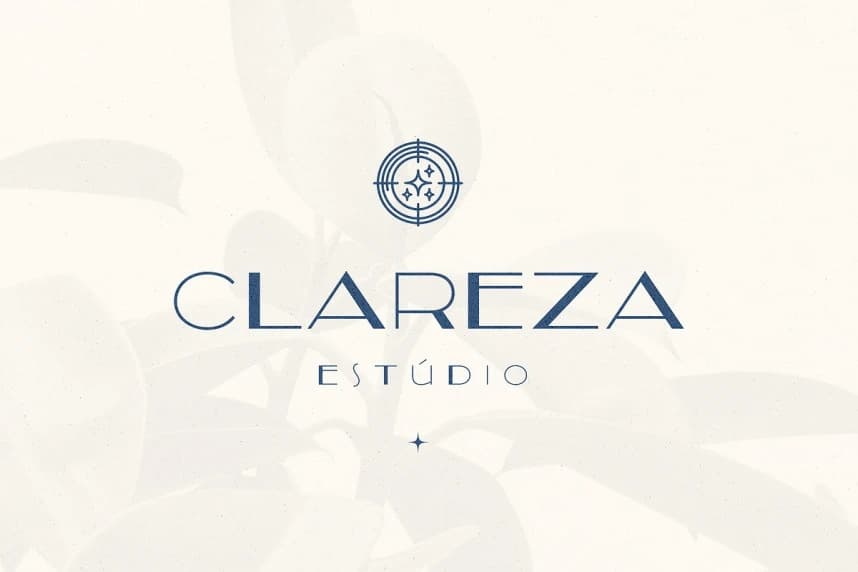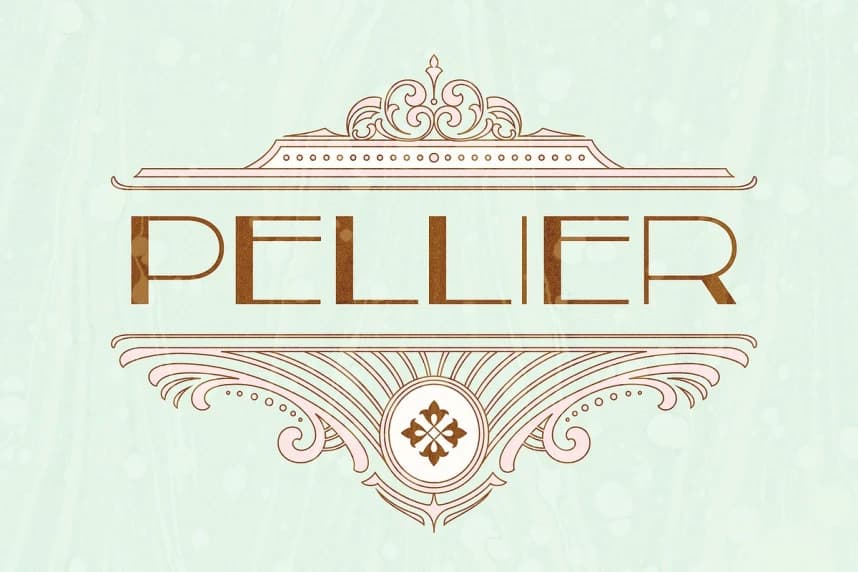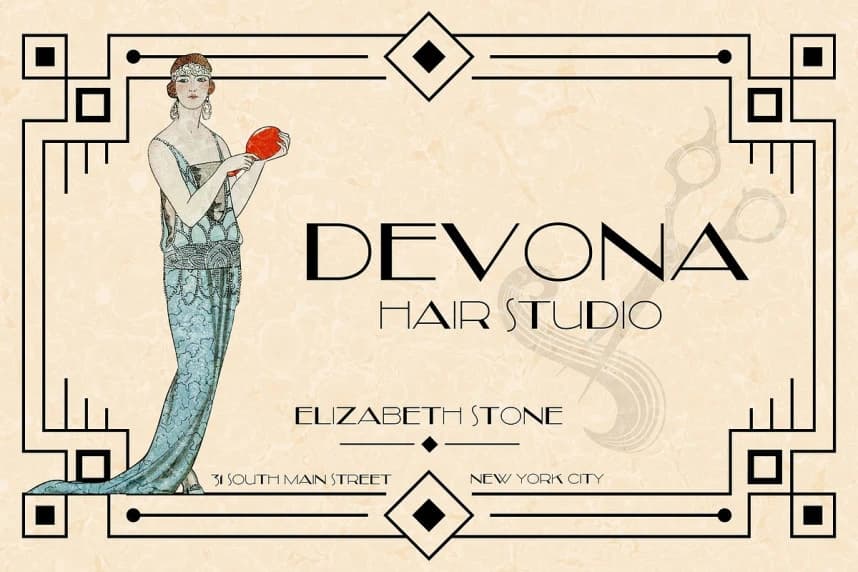
Gatsby Nights Font
Gatsby Nights Font, geçmiş bir dönemin ihtişamını, ritmini ve romantizmini yakalayan çarpıcı bir Art Deco yazı tipidir. Zarif geometrisi, gösterişli eğrileri ve vintage çekiciliğiyle bu yazı tipi, görkemli afiş panolarında ve lüks markalaşmada kendini gösterir.
Gatsby Nights Font, geçmişin ihtişamını, ritmini ve romantizmini yakalayan çarpıcı bir Art Deco yazı tipidir. Zarif geometrisi, gösterişli eğrileri ve vintage çekiciliği ile bu yazı tipi, görkemli afiş panolarında ve lüks marka kimliğinde kendini evinde hisseder
Gatsby Nights
Gatsby Nights Regular